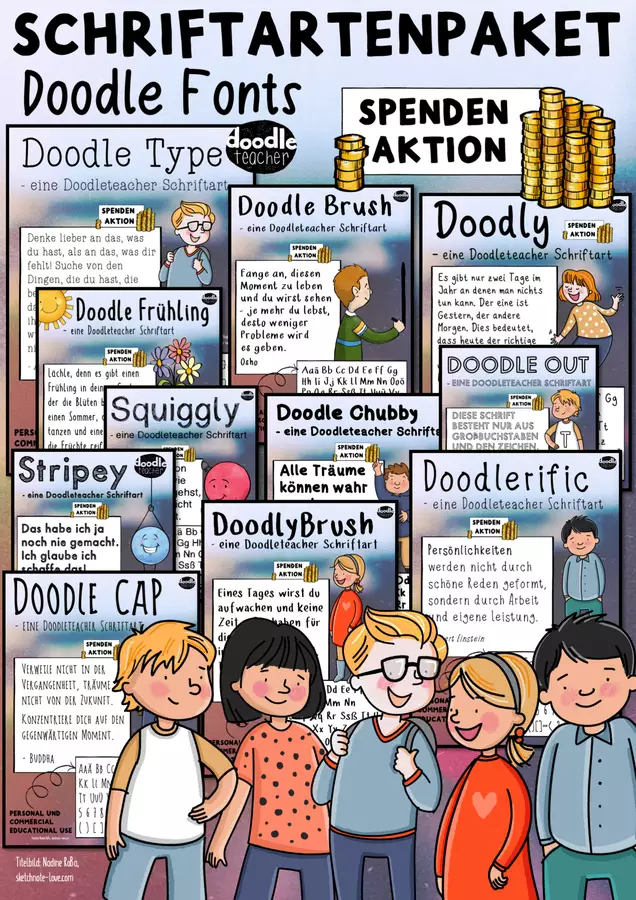
Eine tolle Sammlung an schönen, simplen und spielerischen Schriftarten, auch für die kommerzielle Nutzung (unter Angabe der Quelle).
Folgende Schriften sind enthalten, Paket wächst weiter:
Doodle Frühling - Font / Schriftart
Doodle Chubby - Font / Schriftart
Eine simpel, schöne und etwas dickliche (auf Englisch liebevoll chubby genannt) Schriftart. Gibt es auch im PAKET!Hier gehts zur Spendenaktion
Doodle Cap - Font / Schriftart
Eine sehr schöne Schrift die nur Großbuchstaben besteht (es gibt zusätzlich aber kleinere Großbuchstaben). Sie ähnelt in ihren Grundzügen der beliebten Amatic Schriftart ist aber  etwas freier und doodeliger angelegt. Gibt es auch im PAKET!Hier gehts zur Spendenaktion
Doodle Type - Font / Schriftart
Eine sehr schöne und einfache Schriftart die an einer Type ähnlichen Schrift angelegt etwas freier und doodeliger arrangiert wurde. Gibt es auch im PAKET!Hier gehts zur Spendenaktion